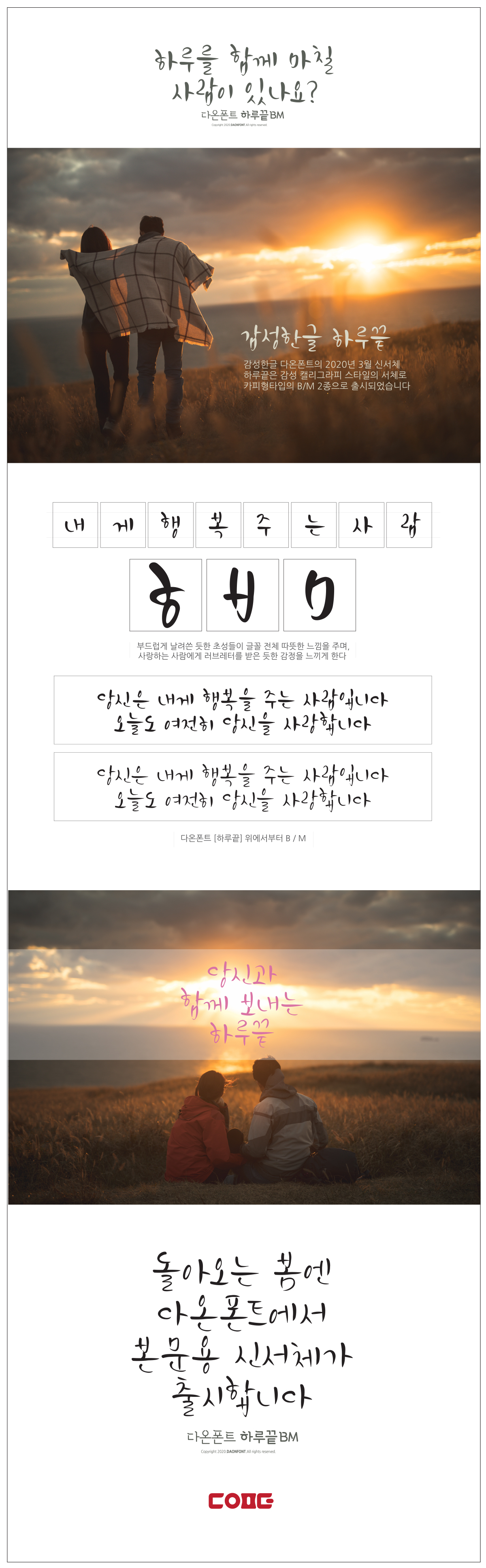
다온폰트 '하루끝'은 2가지 버전으로 출시 되었습니다.
폰트의 구성은 한글 2,350자의 한글과
영문, 숫자, 특수문자 일부로 구성된 폰트입니다.
부그럽게 날쓴 듯한 초성들이 글꼴 전체에 따뜻한 느낌을 주며,
사랑하는 사람에게 러브레터를 받는 듯한 감정을 느끼게 만드는 다온폰트 '하루끝'입니다.